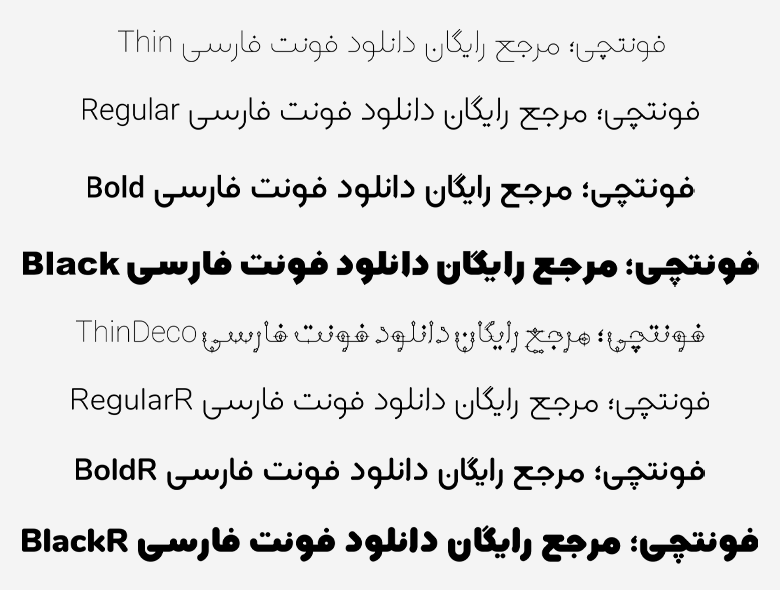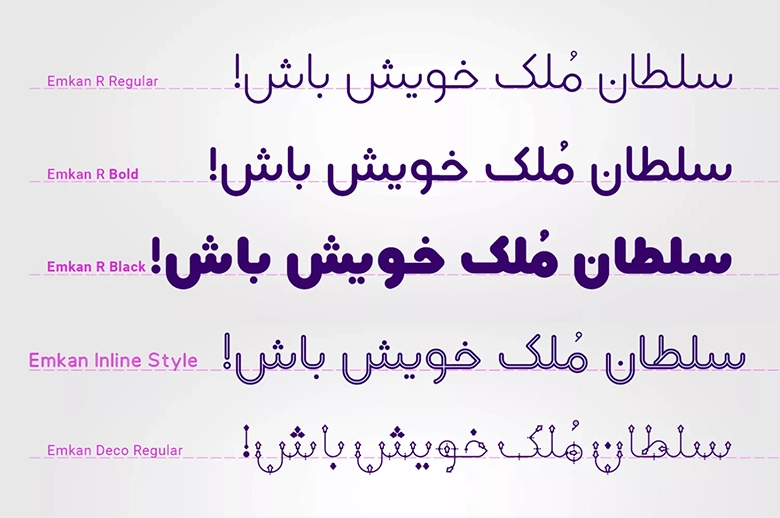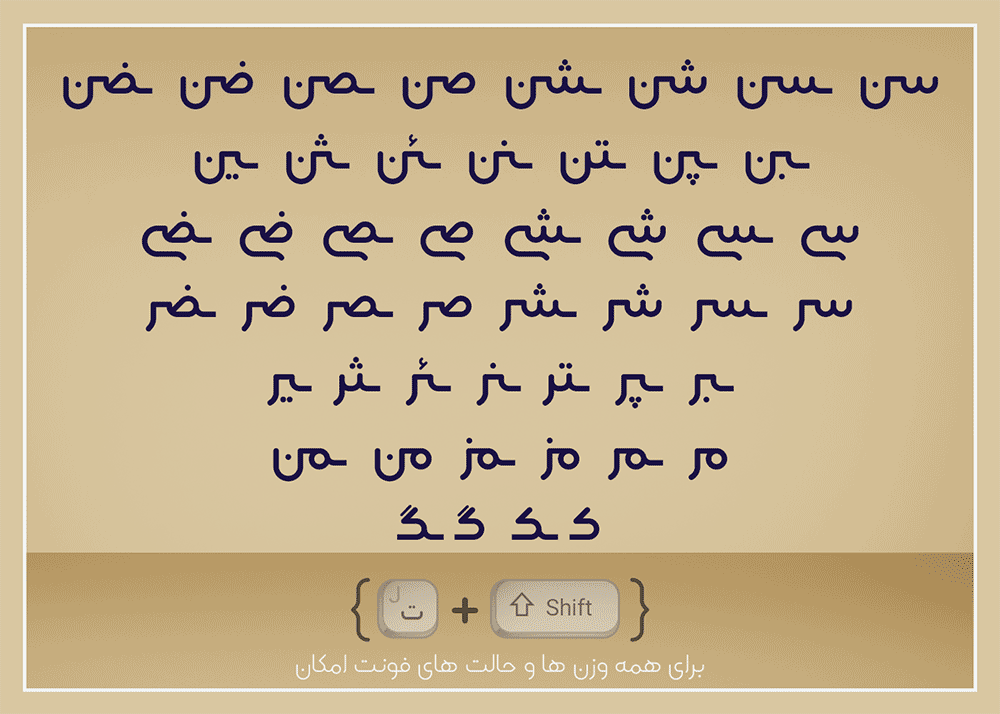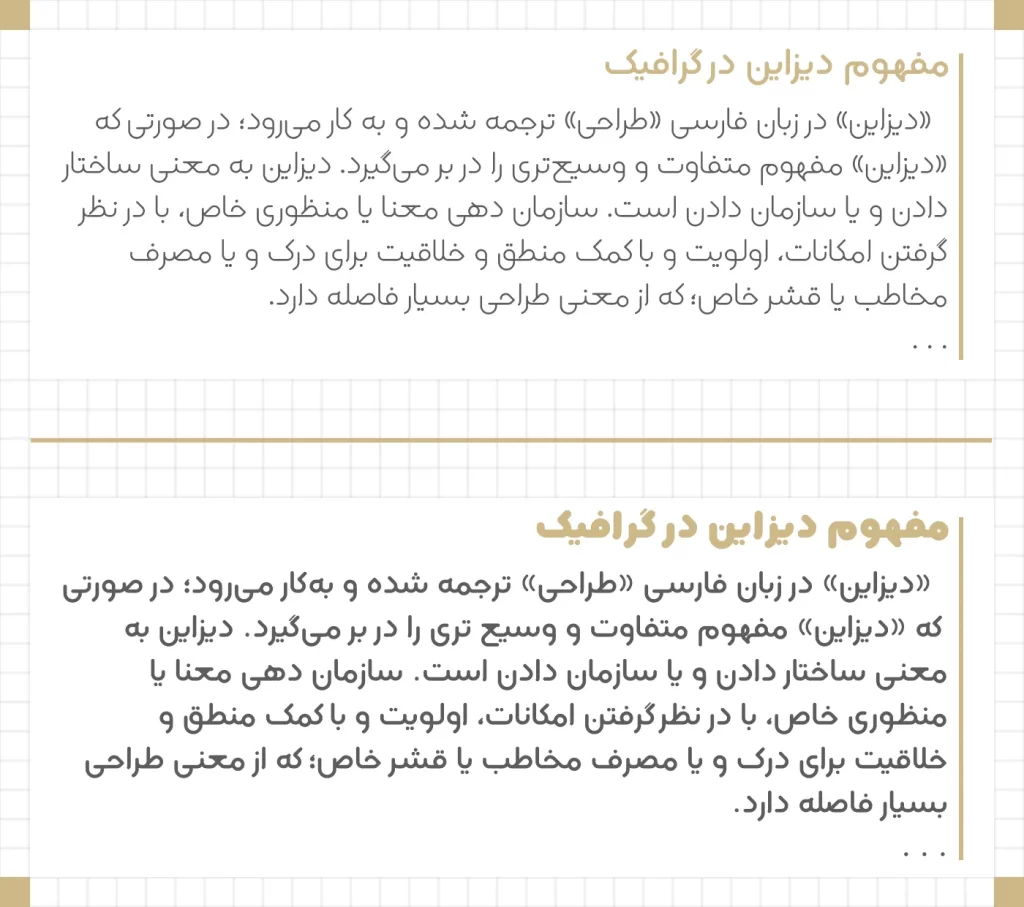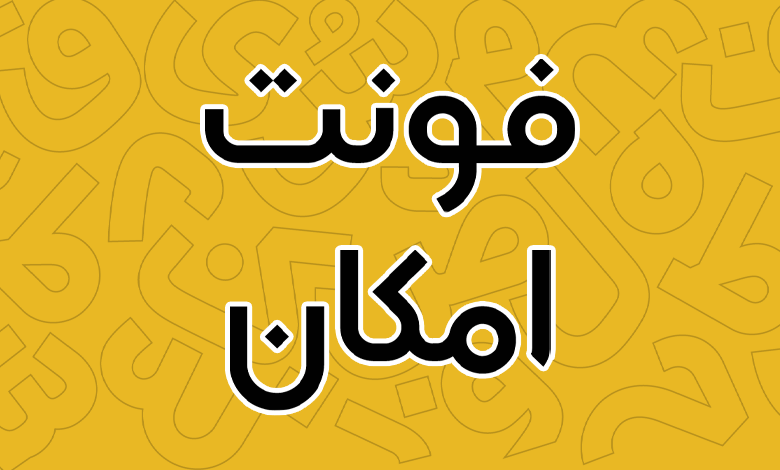
فونت امکان (Emkan)
ابوالفضل رهروان فونت امکان (Emkan) را در قالب یک فونت عنوان و فانتزی مناسب تبلیغات طراحی کرده است که میتواند گزینه بسیار مناسبی برای طراحی انواع بنرها و بیلبوردهایی باشد که در مراکز شهر و مراکز خرید نصب میگردد. این فونت هندسی خانوادهدار دارای اسکلتی خطی است که با توجه به استایل فونت در برخی وزنها کنتراست بالایی را برای خوانایی دارد.
ظاهر یکپارچه و کاملا دهن این فونت در استایل گرد در تمامی بخشهای حروف دارای ضخامت یکسانی است که خود این امر عامل خوانایی و کنتراست بالاتر است که همه این عوامل باعث شده فونتی باشد که برای تاکید روی کلمات کلیدی و مهم یک متن، تاثیر بهسزایی در افزایش خوانایی داشته باشد. در ادامه این نوشته از وبسایت فونتچی به بررسی کامل این فونت پرداخته و در پایان لینک دانلود فونت امکان را در اختیار شما قرار خواهیم داد.
معرفی و بررسی فونت امکان (Emkan)
فونت امکان فونتی نمایشی و مناسب تبلیغات است. از این فونت میتوانید در مطبوعات، طراحیهای تبلیغاتی و هرگونه محتوای بصری که در آن نیاز به فونتی هندسی مناسب برای بهتر دیده شدن عناوین نیاز دارید استفاده کنید. این فونت در ۴ وزن مختلف و در ۳ سبک استایل طراحی شده است.
وزن و استایل فونت مدام
وزنهای فونت مدام شامل نسخههای معمولی (Thin)، معمولی (Regular)، بولد (Bold) و سیاه (Black) هستند. در تمامی این وزنها، حروف دارای پهنای یکسان بوده و شکستگی و انحنای حروف نیز با شدت بالایی در نظر گرفته شده که همین امر به بهتر دیده شدن این فونت کمک میکند.
اما جدایی از وزن، این فونت دارای ۳ استایل مختلف است که میتوانید متناسب با نوع استفادهای که از آن دارید از آنها بهره ببرید. این استایلها شامل استایل گرد (Rounded)، فونت تزئینی بر اساس نازکترین وزن و یک فونت درون خط (Inline) بر اساس حالت گرد هستند که در تصویر فوق هر سه سبک را مشاهده میکنید.
استایل گرد (Rounded) فونت امکان دارای ۳ وزن معمولی، بولد و سیاه است. استایل اینلاین (Inline) فونت امکان دارای ۱ وزن و در نهایت استایل تزئینی (Decorative) فونت امکان دارای ۱ وزن باریک است.
مزایا و ویژگی فونت مدام
فونت مدام جدای از اینکه در مجموع دارای ۹ سبک نوشتاری بر اساس وزن و استایل است، دارای ویژگیهای خاصی هم هست.
اولین مشخصه این فونت که خودنمایی میکند، پشتیبانی از حروف جایگزین است. میتوانید حروفی مثل «ک، گ، ش، پ، ی، ر، ن، ث، م، ص، ض» را در همه وزنها و استایلها به کمک کلیدهای ترکیبی SHIFT + J با استفاده از حروف جایگزین تایپ کنید که در تصویر بالا نمونهای از آن را میبینید.
لازم به یادآوری است که این حروف جایگزین محدود به استایل گرد نبوده و در دو استایل دیگر، یعنی اینلاین و خطی بههمین ترتیب امکان استفاده از حروف جایگزین را دارند.
وجود سبک استایل محتلف در این فونت مزیت دیگری است که باعث میشود بتوان از این فونت به صورت ترکیبی در هر سه سبک متنوع خروجی مناسب و هماهنگی را در عین اینکه استایل متفاوتی دارد بهدست آورد.
برای مثال مشابه تصویر بالا میتوانید از استایل گرد این فونت با وزنهای سیاه یا بولد، برای عناوین استفاده کرده و در مقابل از استایل خطی که ساختاری نازک دارد در متن بلند خود استفاده کنید.
ویژگیهای کلی این فونت عبارتند از:
- فونت مناسب عنوان، تزئینی، فانتزی و مناسب تبلیغات که دارای ساختار هندسی و استخوان درشت است.
- پشتیبانی کامل از زبان فارسی.
- دارای ۴ وزن مختلف و ۳ استایل متنوع گرد، خط نازک و تزئینی که هماهنگی بهتری به متون تبلیغاتی در عنوان و متن خواهد داد.
- امکان استفاده از حروف جایگزین برای حروف مختلف.
استفاده از فونت Emkan برای وب سایت نیز فراهم است و توصیه میشود اگر دارای سایتی محتوایی هستید از این فونت در تیترها، عناوین مطالب و تگهایی همچون H یا نقلقولها از آن استفاده کنید. ساختار فانتزی این فونت شکل زیبایی به متن شما در این بخشها خواهد داد و به کاربر کمک میکند که تمرکز بیشتری روی بخشهای مهم محتوا داشته باشد.
خصوصا در متنهای بلند و طولانی که بسیاری از کاربران شاید حوصله خواندن محتوای کامل را نداشته باشند و صرفا به دنبال بخشی از محتوا در صفحه وب هستند که به آن نیاز دارند. استفاده ترکیبی این فونت در کنار یک فونت متن مناسب در یافتن بخشهای مهم محتوا و تاکید روی پاراگرافهای خاص با این فونت کاربردی است.